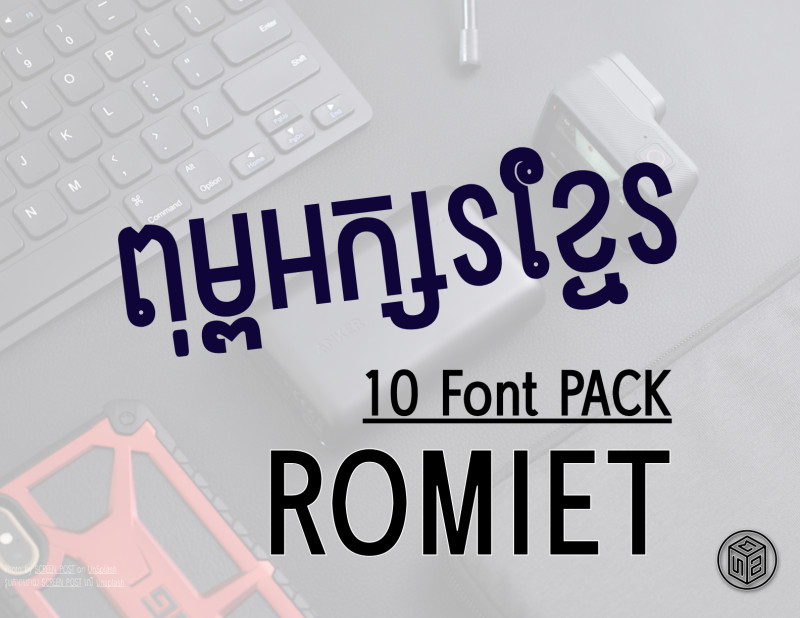
Complete package (10 fonts) set featuring san serif Khmer and Latin letters with true italic variants.
Romiet គឺជាពុម្ពអក្សរទំនើបដែលមានអក្សរខ្មែរ និងឡាតាំងផ្ដល់ដំណើរការបានពេញលេញស្រាប់។ OpenType Features អនុញ្ញាតឱ្យសរសេរជាភាសាខ្មែរបានពេញលេញ និងភាសាឡាតាំងទាំងអស់។
ស័ក្តិសមជាអក្សរការបង្ហាញ ឬក៏អក្សរសរសេរអត្ថបទទូទៅ Romiet គឺជាពុម្ពអក្សរល្អឥតខ្ចោះនូវការសរសេរ ម៉ឺនុយ ផ្លាកសញ្ញាហងលក់ ម៉ាកយីហោទំនើប និង ការផ្សាយពាណិជ្ជកម្ម។
Romiet is a modern font with fully enabled Latin script. The OpenType features enabled to fully write in Khmer and all Latin-based languages.
Suitable as Display or Text font, Romiet is perfect for menus, signs, branding and advertising.